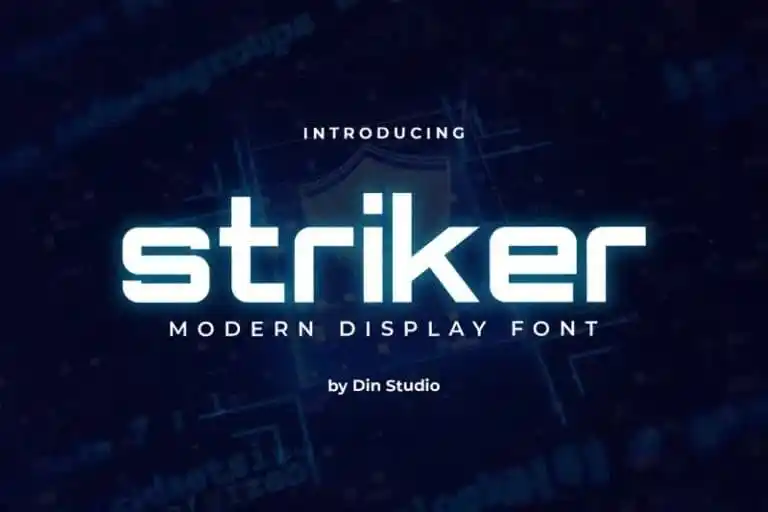
Striker Display Font – Fonte Grátis
Striker Display Font
A fonte Striker Display é perfeitamente adequada para projetos profissionais que exigem um visual atraente e elegante. Com cada letra apresentando uma delicada personalidade única, essa fonte geometricamente precisa é ideal para logomarcas, identidades de marca e citações. Din Studio é o criador desta moderna fonte de exibição, disponível gratuitamente para uso. A utilização deste fonte requer pouca ou nenhuma configuração adicional, pois a fonte está totalmente kerned. Com seu design meticuloso e perfeito em proporções, Striker Display se destaca no meio das outras fontes e é certamente um recurso indispensável para qualquer designer gráfico de topo. Englobando tanto o visual quanto o funcionamento, esta fonte não apenas proporciona uma experiência gratificante ao usar, mas também ajuda a criar visuais profissionais que são fáceis de ler e imediatamente reconhecíveis.